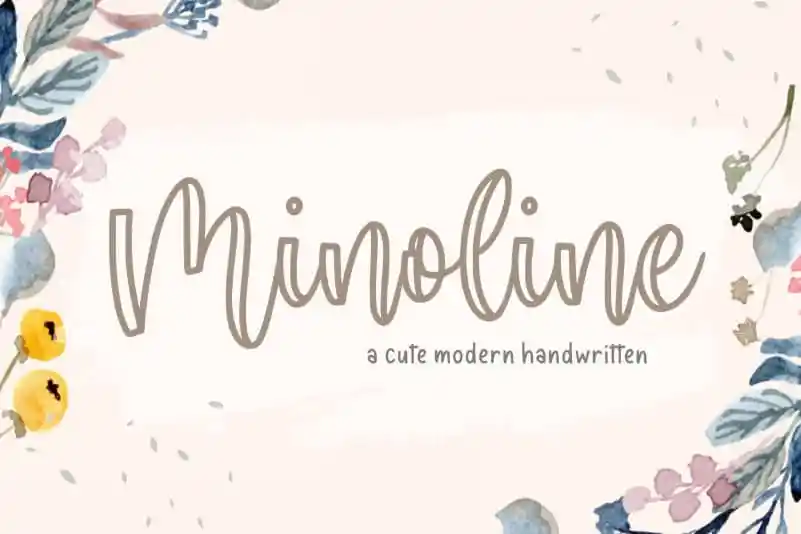
Minoline Cute Modern Calligraphy Font – Fonte Grátis
Minoline Cute Modern Calligraphy Font
A Minoline é uma linda fonte de calligrafia que se destaca por sua elegância moderna e charmosa. Perfeita para criações digitais, a Minoline oferece um toque personalizado perfeito para projetos como embalagens de produtos, marcações, revistas, redes sociais, casamentos ou simplesmente para destacar palavras sobre o fundo. Seu design minimalista e harmonioso se adapta às mais diversas necessidades digitais sem deixá-las parecerem fortes demais ou fracos demais. A Minoline é uma escolha inteligente para aqueles que buscam um toque de sofisticação em suas criações digitais, tornando-a a fonte ideal para qualquer projeto visual. Com a Minoline Cute Modern Calligraphy Font, seu design digital adquirirá o charme e a personalidade necessária para destacar-se da multidão.